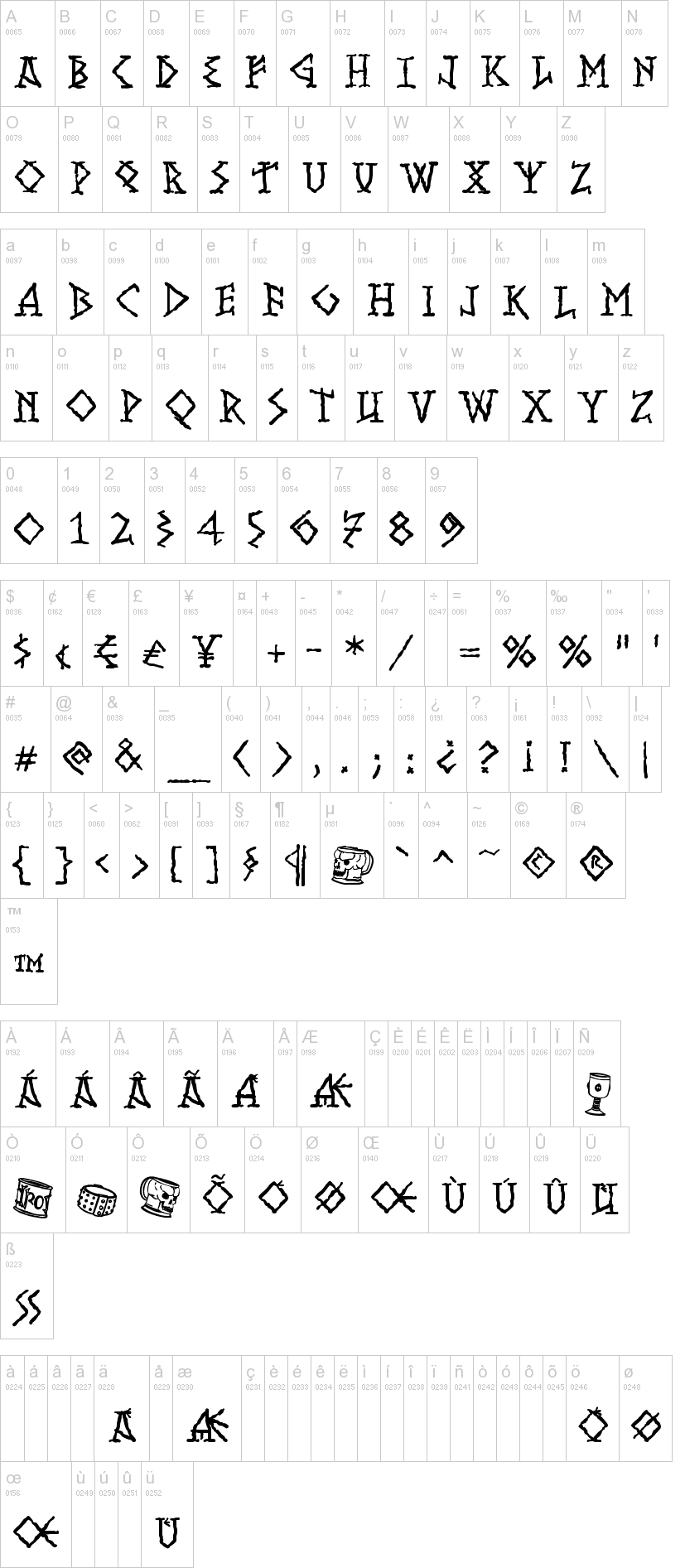
Runish MK
Runish MK是一种基于古代符文文化的字体。它的设计灵感来自于北欧符文、盎格鲁-撒克逊符文和高盧符文等古代符文。Runish MK字体具有浓厚的中世纪风格,常用于设计游戏、电影、书籍和其他创意设计项目中。 Runish MK字体包括26个拉丁字母和23个古代符文字符。该字体的特点是粗犷有力、线条粗细不一,同时也具有一定的神秘感和古老的氛围。运用Runish MK字体可以为设计作品增添一份神秘感,展现古代符文文化的魅力和独特的历史底蕴。 Runish MK字体是一种免费的字体,可以在多种文本编辑和排版软件中使用。如果您对于古代符文文化感兴趣,或者需要为您的创意设计项目增添一份中世纪风格,那么Runish MK字体将是一个非常好的选择。
Runish MK是一款非常不错的手写艺术字体,具有很好的视觉感,适合于文化类的宣传设计、商业类品牌的广告和产品包装设计以及个性化文字排版等较多场景。